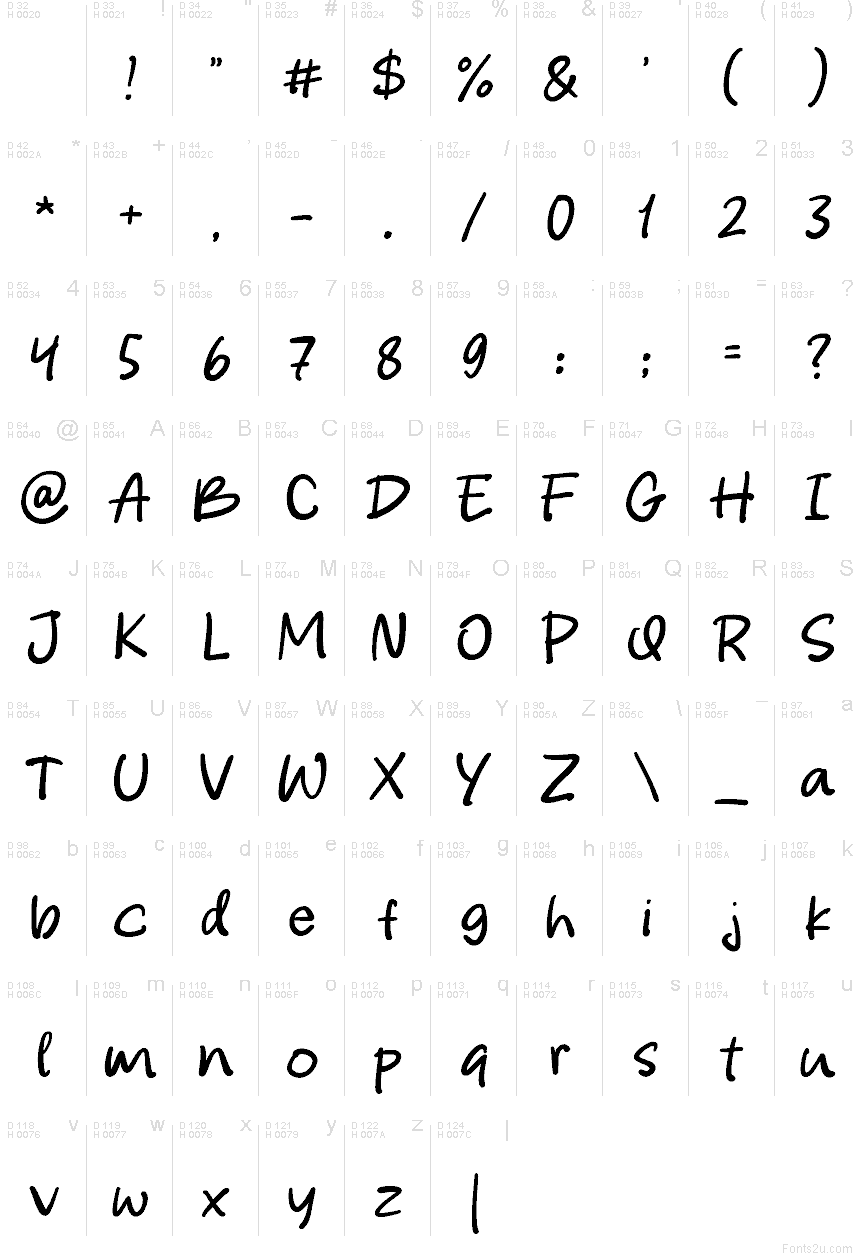
Taste Bread HD autorstwa Khurasan to darmowy pędzlowy krój pisma o szerokich, płynnych pociągnięciach i swobodnym wykończeniu przypominającym marker. Zaokrąglone łuki i nierówna grubość linii sprawiają, że litery wyglądają na szybko narysowane, a nie starannie złożone. Wysokie, proste elementy są szczególnie żywe.
Jego zamaszyste linie mogą nawiązywać do odręcznych ilustracji jedzenia, co czyni go naturalnym wyborem do opakowań piekarniczych i identyfikacji wizualnej kawiarni. Nieformalne kształty sprawdzają się również na kartach z przepisami i grafikach do mediów społecznościowych, gdzie litery mogą wnieść ciepło odręcznej notatki. Jego najsilniejszym kontekstem jest swobodny design związany z jedzeniem i napojami, w szczególności projekty skupione na chlebie, domowych potrawach lub produktach z małych serii.